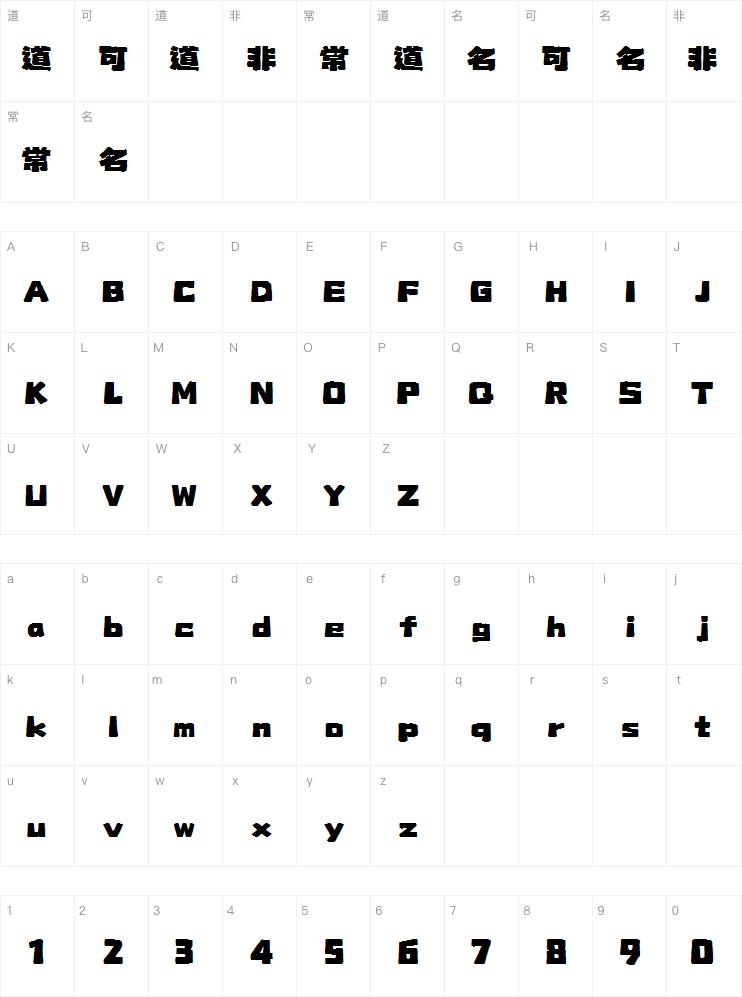
上首呆鹅体
上首呆鹅
上首呆鹅体,简体中文约6763字,“上首呆鹅体”是一款兼具呆萌气质与艺术美感的原创字体。字体设计以饱满的线条为基础,笔画排列带有一种随意的灵动之美,既不拘一格又不失协调感。整体字形看似天真憨厚,却又蕴含着独特的设计巧思,给人以耳目一新的视觉体验。它打破了传统字体的严肃与刻板,将趣味与个性融入到每一笔每一划之中。这种独特的风格使“上首呆鹅体”成为表现创意、传递轻松氛围的绝佳选择,无论是品牌设计、文化传播还是日常应用,都能轻松吸引目光,展现与众不同的艺术感染力。